逐浪曲角飘香食丼体是逐浪字库推出的一款中文艺术字体,字线偏粗,笔画夸张,多花边。字体大胆引用日系漫画粗体的设计,横折弯勾,避免少直线。整个字库有如一个大型的牛角,上翘的曲线造型,强烈的异域网格。特别适合酒肆、夜场、餐饮、宾馆、建筑等领域。
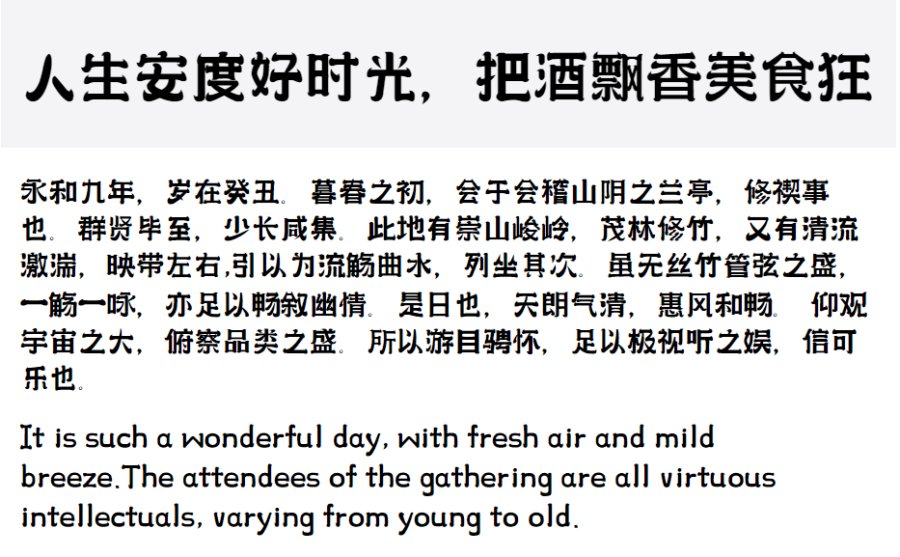
汉标小艾双钩简体是汉标字库推出的一款逗趣可爱、动感活泼的创意美术标题字。它的字形变化多样,笔画掏空,粗细对比强烈,组合起来富有节奏感.字形多变,依据字体结构而呈现出或长或方的节奏变化,十分俏皮可爱。
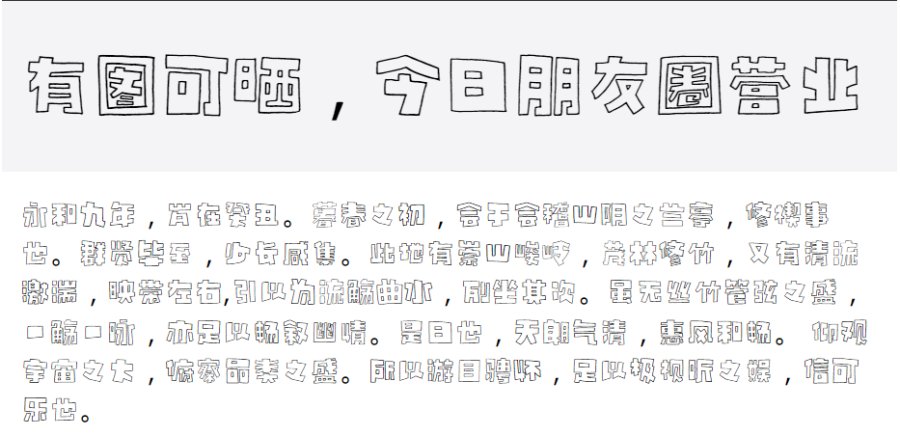
三极三角赋简体是三极字库出品的一款艺术字体,该字体笔画粗细不一,部分笔画处较粗并略有倾斜感,使得字形生动活泼,整体风格使用儿童书写的轻松随意,可爱随性,并且中英文、阿拉伯数字全面支持,可以很好的应用于文本装潢、信息展示、网页设计、篆刻制模、数据制作、装潢设计、计算艺术设计、视觉设计、字帖等一切合法应用场景,有喜欢的朋友可下载收藏。